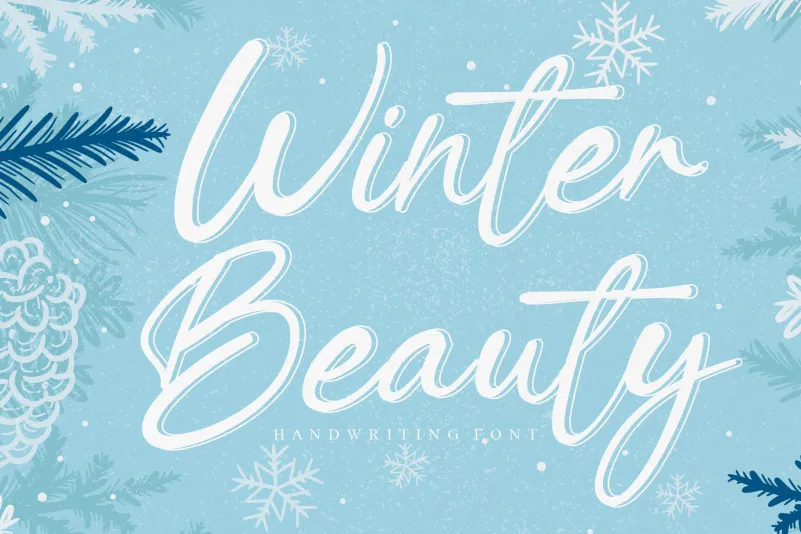
Winter Beauty Script Font – Download Grátis
A Winter Beauty Script Font é uma fonte de script moderna criada por andikastudio. Suas características naturais e únicas a tornam perfeitamente adequada para um vasto leque de designs. A única restrição é sua imaginação, permitindo-lhe explorar inúmeras possibilidades. Seja para criar anúncios envolventes, folhetos exclusivos ou até mesmo elementos gráficos para suas publicações online – esta fonte cativante e versátil está disponível para que você possa expressar seu design de maneira única. A Winter Beauty Script Font é uma escolha ideal para designers criativos que procuram um toque refinado e único em seus projetos.